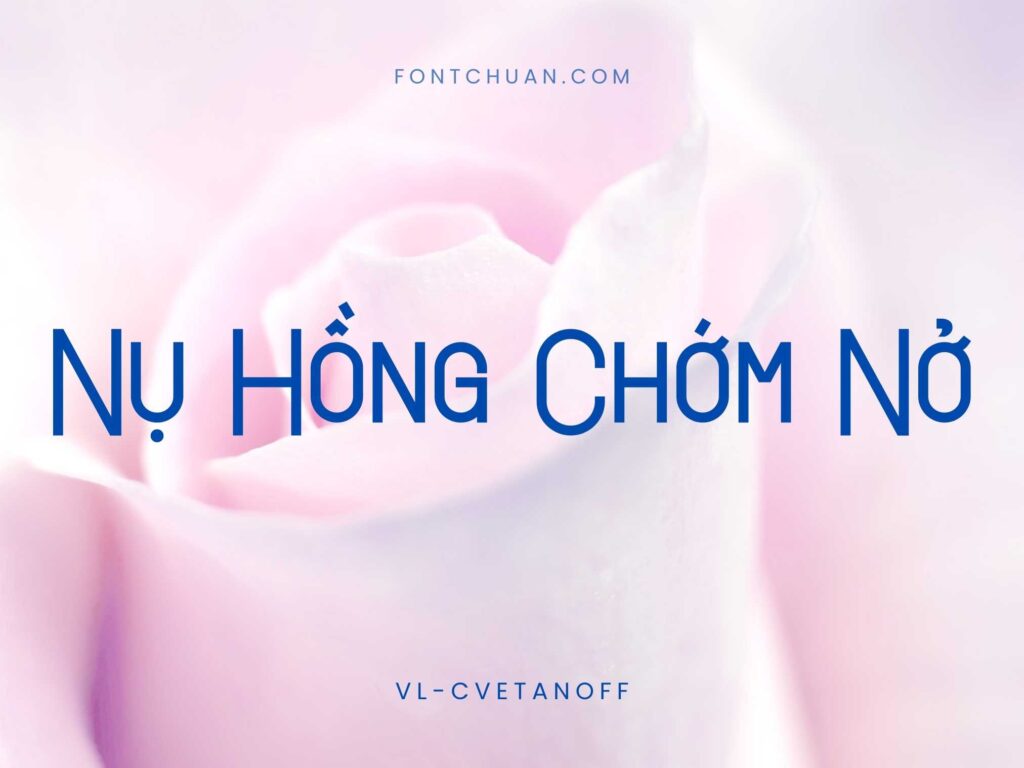
Font VL Cvetanoff Việt Hóa
Tác giả Font: Vpcreativeshop
Việt hóa bởi: Font Việt Linh
VL-Cvetanoff là một phông chữ sans-serif hiện đại, được thiết kế bởi VPcreativeshop. Phông chữ này nổi bật với các đường nét đơn giản và tinh tế, tạo nên sự chuyên nghiệp và dễ đọc trong các thiết kế. VL-Cvetanoff đã được Việt hóa bởi Việt Linh, hỗ trợ đầy đủ các ký tự tiếng Việt, giúp người dùng dễ dàng áp dụng trong các dự án sáng tạo. Phông chữ này được thành viên Font Chuẩn sưu tầm và đăng tải nhằm phục vụ nhu cầu thiết kế đa dạng.
Với thiết kế rõ ràng và linh hoạt, VL-Cvetanoff phù hợp cho các ứng dụng như tiêu đề, văn bản dài, thiết kế logo và các ấn phẩm in ấn. Trong lĩnh vực sự kiện, phông chữ này có thể được sử dụng trong các dịp như lễ hội, thiệp cưới và các sự kiện văn hóa. Ngoài ra, VL-Cvetanoff cũng thích hợp cho các ngành nghề như quảng cáo, giáo dục và công nghệ.